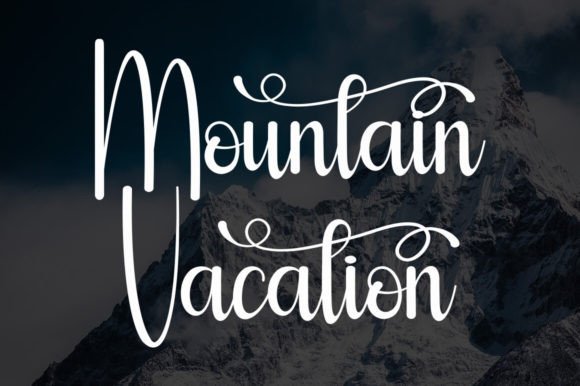
Mountain Vacation
Jika anda sedang mencari aset berkualiti tinggi seperti Mountain Vacation, pakej premium ini merupakan pilihan yang hebat untuk projek kreatif anda.
Sama ada anda mencipta produk POD (Print on Demand), jemputan perkahwinan atau grafik media sosial, Mountain Vacation amat bersesuaian.